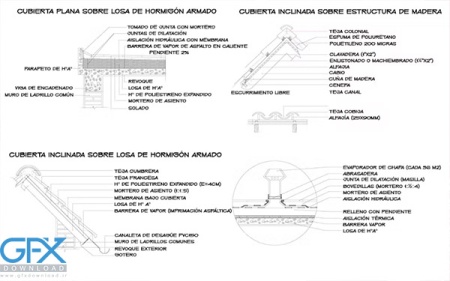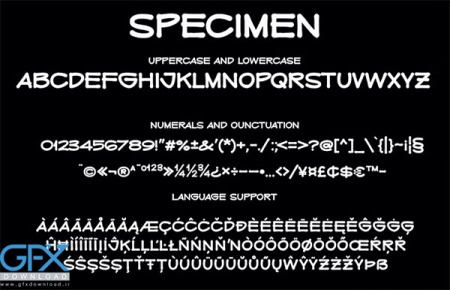
دانلود فونت دست نویس SNATCHED
دانلود فونت دست نویس معمولی SNATCHED
دانلود فونت دست نویس SNATCHED یک فونت دست خط با طراحی زیبا و بی نظیر است. این فونت از حروف بزرگ و کوچک یکسانی تشکیل شده است که اغلب به آن "همه حروف بزرگ" گفته می شود و با اعداد و علائم نگارشی کامل می شود. ترکیب به شکلی است که بیشتر شبیه دستخط معمولی معماران است. این فونت به نظر می رسد که با یک نشانگر یا قلم فنی نوشته شده باشد، بسیار پررنگ و شیک و خوانا.
فونت انگلیسی دست نویس SNATCHED
فونت انگلیسی دستخط معمولی SNATCHED
دانلود فونت انگلیسی دست نویس SNATCHED
فونت انگلیسی دست نویس SNATCHED برای طراحان با طراحی بسیار طبیعی و ریتمیک به نظر می رسد تا ارائه ها و چاپ های آبی را زیبا کند. قابل نصب برای برنامه های CAD، Sekthup و سایر برنامه ها. این فونت برای رسانه‌های مختلف مرتبط با دست‌ساز، مشاغل صنایع دستی، آرم‌ها، نقل قول‌ها، چاپ‌ها، پست‌های رسانه‌های اجتماعی، کسب‌وکار مستقل، ورزش‌های فضای باز و سایر برنامه‌ها بسیار مناسب است تا احساس دست خط را تقویت کند و توجه را جلب کند.